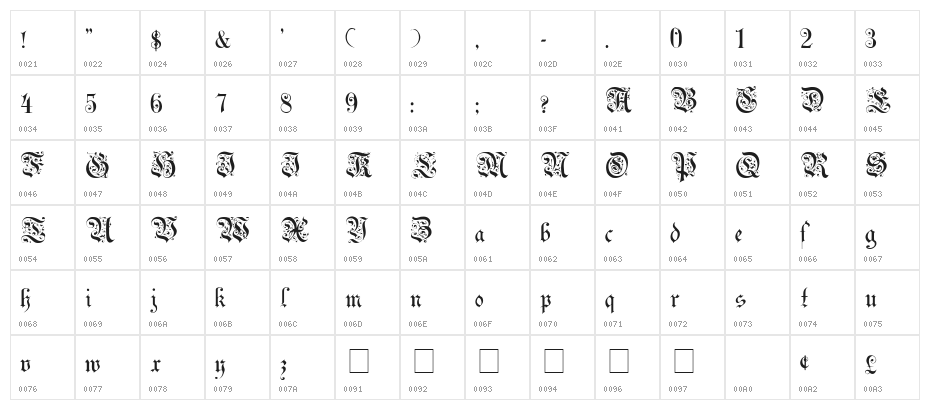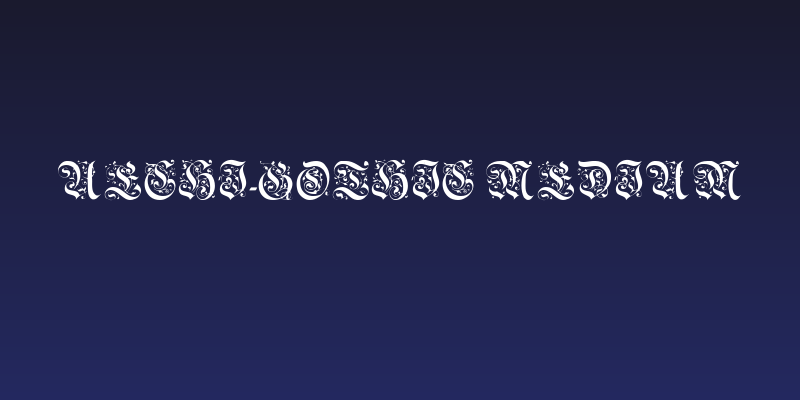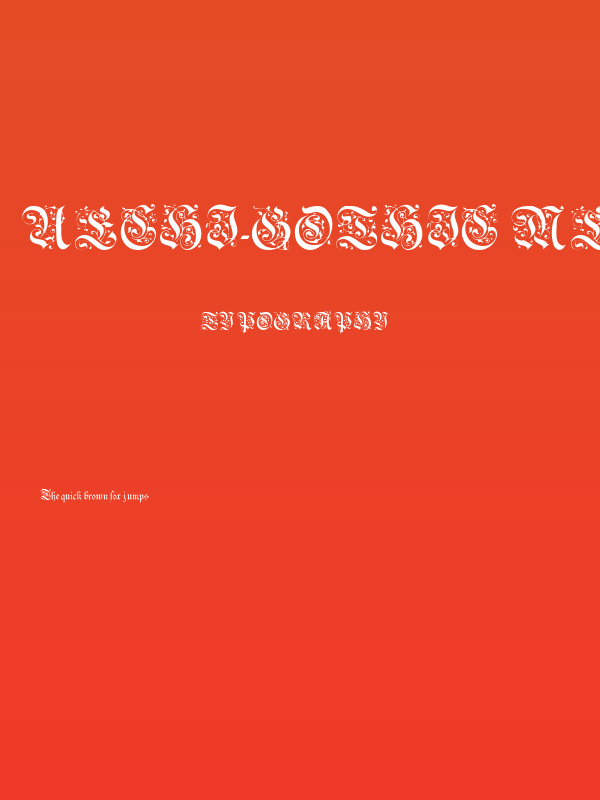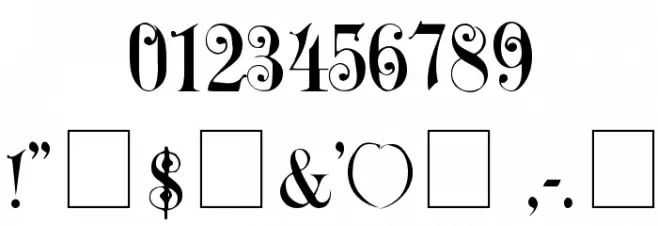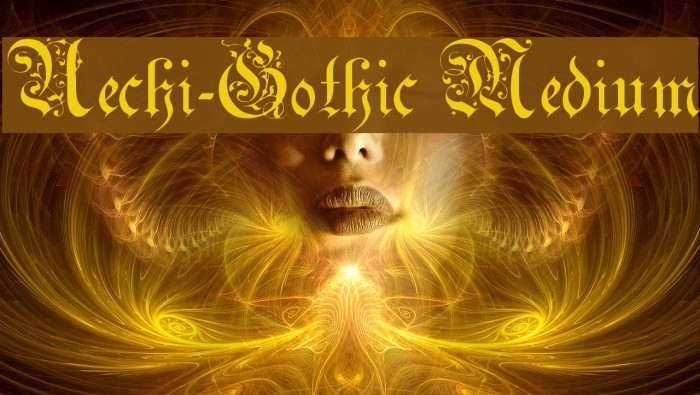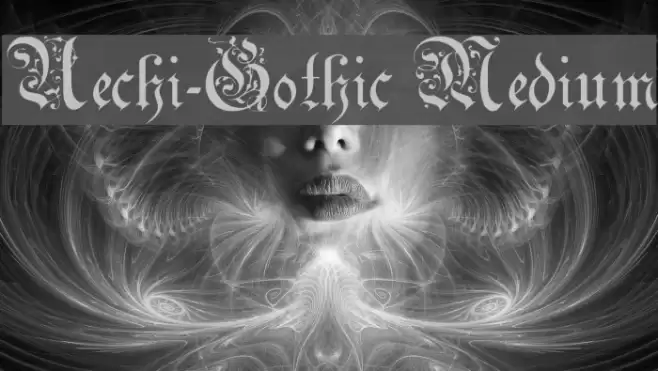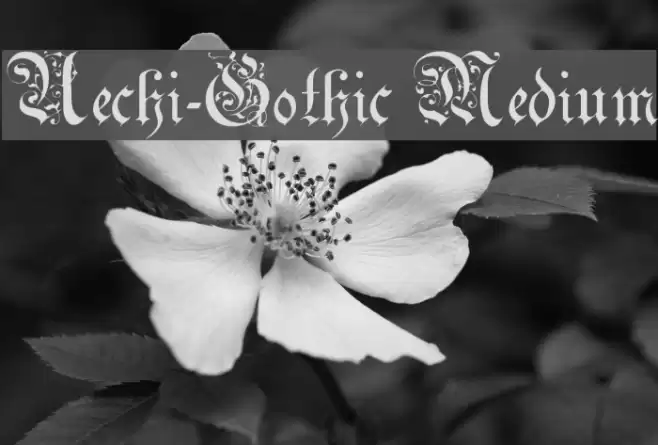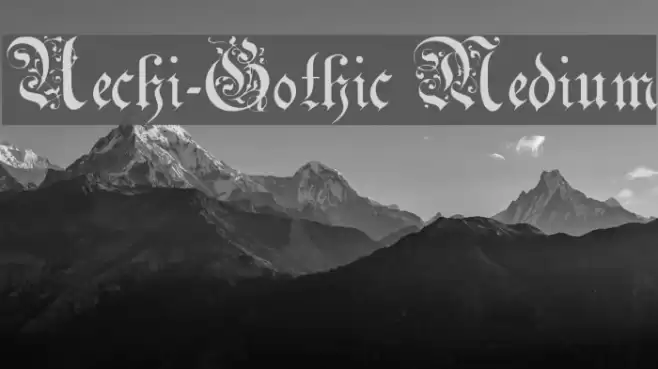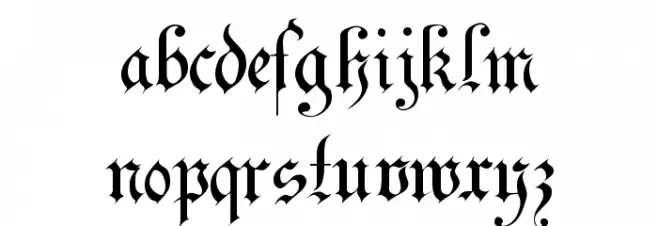
Uechi-Gothic Medium Font
Fonts by David Rakowski
| Projets proposés | Ideal for wedding invitations, historical-themed posters, branding for luxury products, or any project needing a classic and sophisticated touch. |